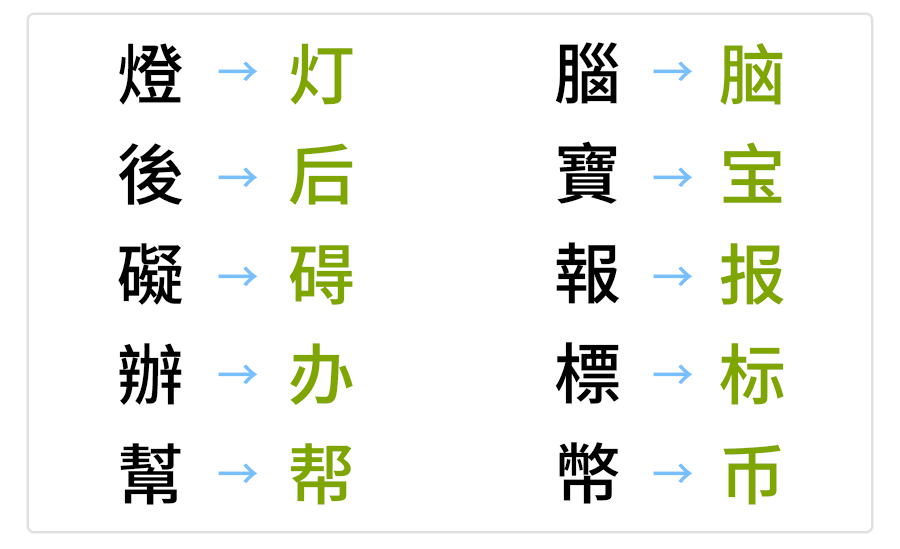
20世纪初,随着中国社会的变革,文字简化运动逐渐兴起。为了提高国民的识字率和推广普及教育,中国政府从1950年代开始推行汉字简化政策。1956年,中国政府正式颁布《简化字总表》,确定了一系列简化字形。自此,简体字成为中国大陆的官方书写标准。
简化字,又称简体字,是指对繁体字进行简化后的汉字形式。简化字的产生和发展主要是为了提高书写效率和推广普及教育。简化字的简化方式通常包括减少笔画数、改变字形结构等,使汉字更易于书写和辨认,但不改变汉字的基本含义和读音。
简化字的雏形可以追溯到秦汉时期的草书和隶书。草书是一种行书,笔画简化,书写迅速。隶书则是在草书基础上形成的一种规范化书写方式。这些书写形式的出现为简体字的产生和发展奠定了基础。
自汉字产生以来,繁简字体一直共存。在宋朝以后,繁体字逐渐成为官方和正式场合的书写标准,而简体字在民间广泛流传,成为日常书写的主要形式。